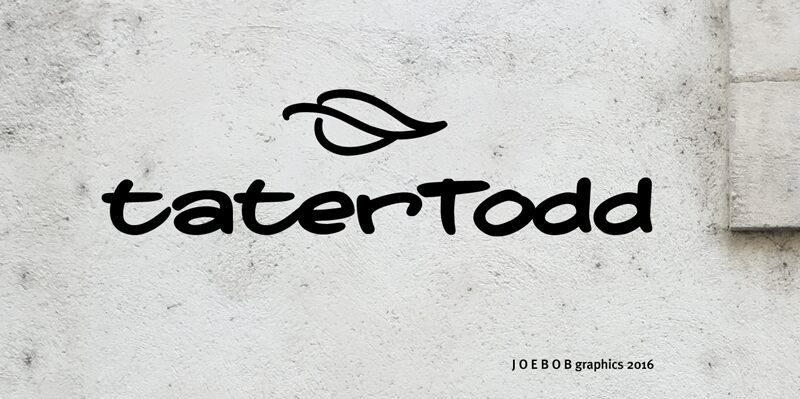
To jest wersja próbna taterTodd, szerokiego pisma typu brush, kreślonego grubym pisakiem, o czytelnym i przyjaznym charakterze. Świetnie nadaje się do menu, a w swoich projektach koniecznie wypróbuj zapis wyłącznie wielkimi literami. Pełna wersja z możliwością osadzania dostępna jest tutaj: https://www.joebobgraphics.com/fonts/tatertodd/
taterTodd TRIAL
taterTodd Regular is a font by JOEBOB graphics, designed by JJW van der Ham in 2016.